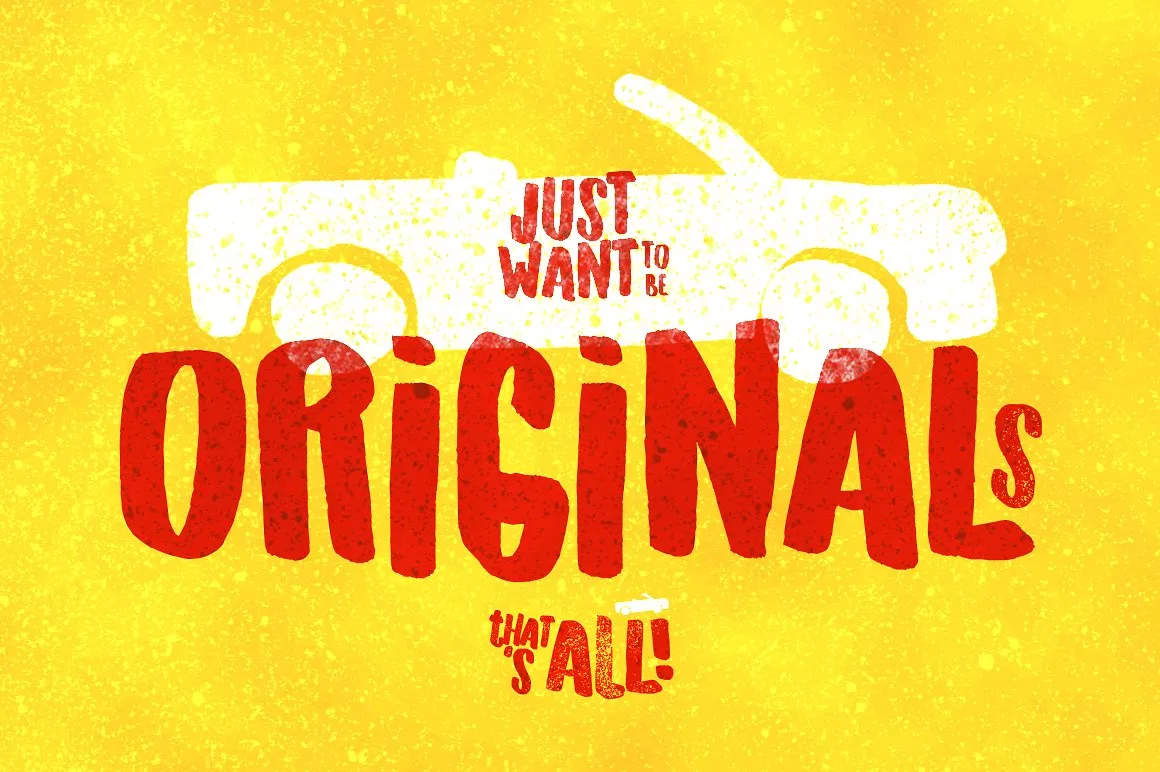
Originals Typeface – Download Grátis
Introduzimos Originals Typeface! Originals foi criado pela LeoSupply.co, uma fonte premium que você encontrará para venda na plataforma creativemarket. Agora, ela está disponível gratuitamente para download hoje. Originals Typeface é um tipo de display desenhado a mão com um toque leve e descontraído. É perfeito tanto para uso em rótulos de prateleira, camisetas ou cartões, quanto para ambientes de design que retratem uma temática fresca de verão. Seja você quem estiver criando letras dinâmicas ou um texto casual, Originals Typeface é certamente o tipo certo para levar seu projeto ainda mais longe.